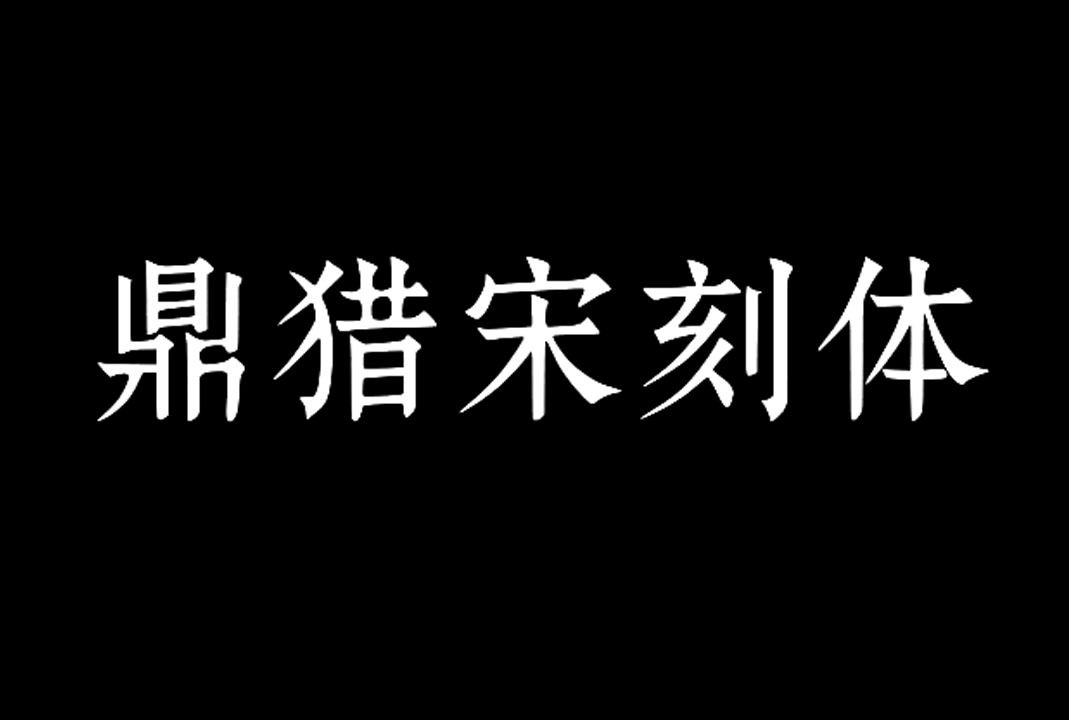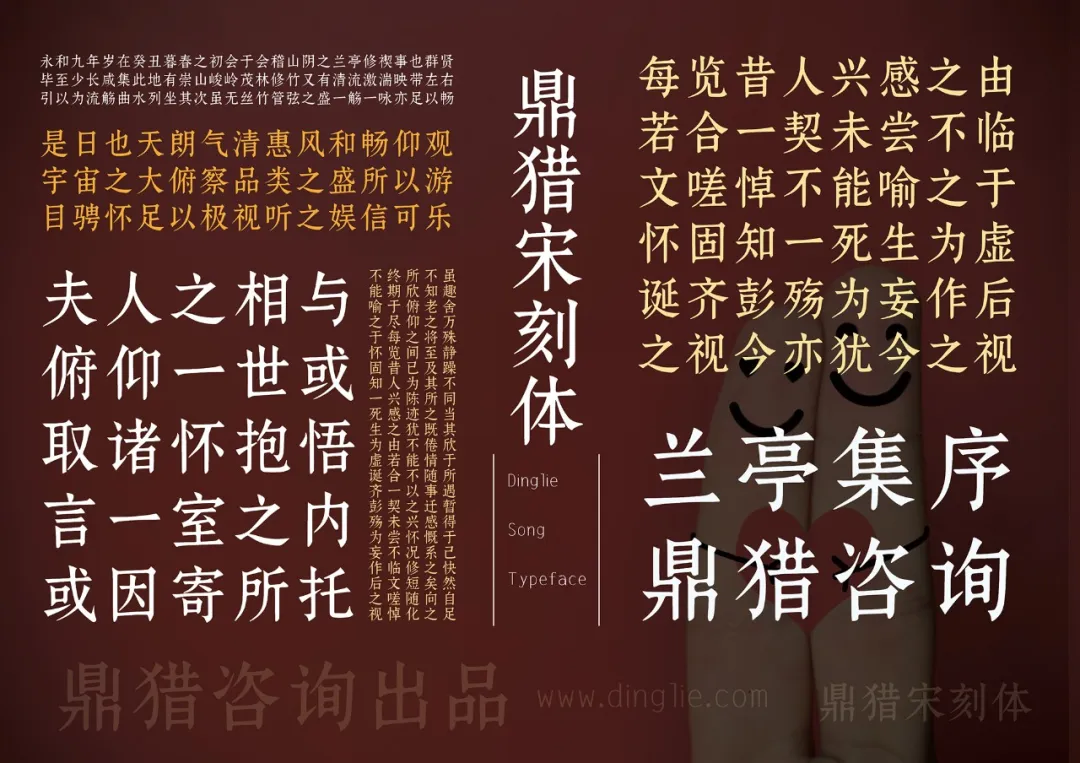
鼎猎宋刻体是由鼎猎咨询于微信公众平台发布的一款免费中文字库,该字形结体谨严,笔画顿挫感明显,文理坚致有韧性,版式疏朗雅洁,应用场景广泛,适合多种行业。
鼎猎宋刻体以简体中文汉字编码国家标准(GB2312编码)为标准,共计设计了多达7415个字符,其中汉字6769个。可以满足绝大部分印刷设计等要求。